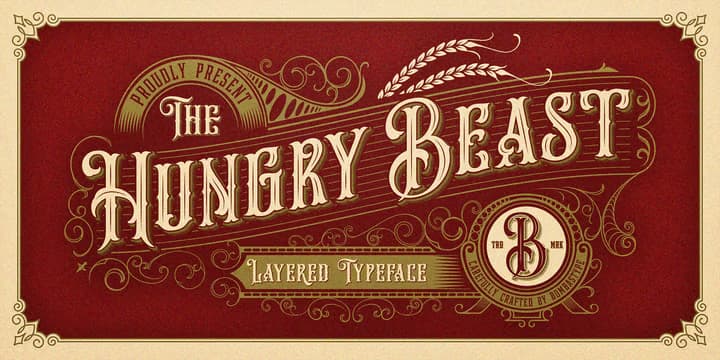
Hungry Beast
ヴィクトリア朝スタイルのデコラティブなディスプレイ。セリフがタスカン(魚尾型)の植物的なニュアンスがふんだんに施されたディスプレイで、往時の雰囲気満載のレトロな書体である。レイヤードになっており、インラインやシャドウスタイルのものを重ねて色分けすることでアレンジでき、かつオーナメント類も付属しているので、好きなだけデコる事が可能。小文字はなくスモールキャップス。1ウェイト。